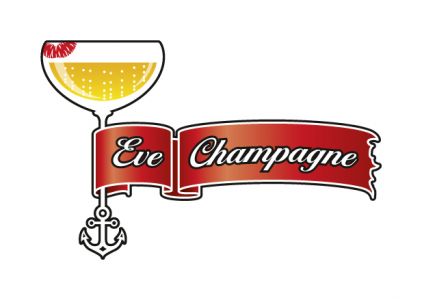
Elegante, Edel anmutende Serifenlose als Kontrastschrift.
Ich habe ein Logo für eine Tänzerin gemacht. Es ist recht rustikal und plakativ. Als Logoschrift habe ich die "Ballantines" verwendet, da sie eine kompakte Script ist.
Jetzt suche ich eine elegante, edel und wertig anmutende Serifenlose Schrit, als Kontrast zu der Scriptschrift.
Ich habe mal mit Avantgarde und Gotham herumgespielt. Bin aber nicht wirklich zufrieden. Zur Zeit tendiere ich zur Avantgarde. serifenlose Antiquas wirken generell oft etwas "unspektakulär".
Lesefreundlichkeit sollte nicht im Vordergrund stehen, da die Schrift außerhalb von kleineren Mengentexten nicht vorkommen wird.
Was haltet ihr von den DTL-Schriften Documenta, Caspari und Nobel? Würd gerne eine andere Schrift als Avantgarde nehmen...
rustikal und ballantines kannich mir zwar nicht vorstellen,
aber zeig doch mal deinen entwurf, ggf. können wir dir so besser helfen.
eine avantgarde würde ich nicht mit der ballantines mischen.
die »ballantines« ist zwar nicht der super bringer, mit der serfienlosen (ich nehme an für eine unterzeile?) kannst du nicht viel rausholen, je klasicher desto besser, ich würde die akzidenz grotesk probieren.
ohne das logo zu kennen und zu wissen was du mit zweiten schrift machen möchtest ist es aber schwer.
Jetzt suche ich eine elegante, edel und wertig anmutende Serifenlose Schrit
serifenlose Antiquas wirken generell oft etwas "unspektakulär"
sollte es nicht so sein?
Ballantines ist dafür wohl a) sehr klischeehaft und b) sehr verstaubt, aber vielleicht oberflächlich naheliegend.
Der Charakter solcher Künstlerschriften geht sehr gut mit klassizistischen Antiquas zusammen, also würde ich wohl eine ›Linearantique‹ testen, die aus dieser Form der Antiqua entstanden ist und da fällt mir als erstes die Univers ein.
Gotham geht in Richtung in Avant Garde ›ist‹ konstruiert. Wenn du sowas suchst, dann wäre die Avenir eine Überlegung wert. Im Moment sehr im Trend und mein erster Gedanke wäre die Neutraface von Houseindustries gewesen. Aber ich hätte das Gefühl, dass sich eine Univers oder eine Avenir besser mit der Ballantines vertragen würde.
Hab mich wohl etwas falsch ausgedrückt.
Ich zeige das Logo jetzt einfach:
Dass Ballantines abgenutzt und klischeehaft ist, wusste ich nicht. Dazu kenne ich mich noch nicht genügend mit Schriften aus.
Ich hatte auch überlegt, dass man die Ballantines ausschließlich im Logo behält und für Texte/Überschriften eine andere Script nimmt (Dalliance?). Denn die Ballantines hat sich schlicht gut in dem Logo gefügt, aus bereits vorher genannten Gründen (kurze Unterlängen, kompakt). Die Textschrift soll für Infotexte, Leporellos, Flyer eingesetzt werden, also Hausschrift werden.
Ich finde die DTL Nobel sehr schön (geht ja in Richtung Avenir). Die spitzen VErsalien strahlen etwas frechen aus. Außerdem erinnert mich die Condensed an Anzeigen und Plakate der 50er Jahre, was für die Figur "Eve Champagne" sehr passend wäre.
Der Begriff Tänzerin mag etwas weit sein. Sagen wir "Burlesque-Tänzerin".
was ist den das für eine tänzerin? :shock:
Schade, daß es die Elegant-Grotesk nicht digitalisiert gibt, oder?
Gruppe VI - Serifenlose Linear-Antiqua - Elegant Grotesk halbfett
D.Stempel AG, Frankfurt am Main
Erstguß 1928
Gustav Möhring
Preußischer Mann von Welt.
also mir gefällt das logo gut. das glas ist mir zwar einen hieb
zu groß ... aber darum gehts ja nicht
*
die idee mit der dalliance finde ich gut, ggf. würde ich aber den spieß
rumdrehen – also dalliance fürs logo und ballantines für headlines.
ggf. auch auf ballantines verzichten und einen mix aus dalliance +
dalliance script verwenden. das die ballantines abgenutzt ist, finde ich nicht.
da gibts andere 'englische schreibschriften' die man zu oft sieht.
eine dalliance würde allerdings dem logo mehr charakter geben.
schau dir mal die sterling von canada type an:
http://www.canadatype.com/showfont.php?id=77
die hat durch die alternativen noch mehr charakter.
* es geht ja um die textschrift.
hast du dich mal weiter bei emigre umgesehen?
eidetic neo: http://www.emigre.com/EF.php?fid=91
gibts auch als eidetic modern:
http://www.psyops.com/html/spec_eidetm.html
ich würde nicht zu neutral werden (univers, akzidenz ...) sondern
irgendetwas edles, jedoch lesbares, verwenden.
vielleicht auch die vista von emigre oder die ff strada.
nur nicht zu technisch ...
Naja, Kritik zum Logo nehme ich natürlich auch entgegen, da es durchaus noch verbessert werden kann...
Ansonsten:
Sehr schön.
Obwohl: Mir gefallen die Gemeinen noch besser als die Versalien.
Ja, die Versalien sind halt leichter zu konstruieren. Wenn ich abends mal wieder ein bißchen ausspannen will, mache ich mich mal an die Kleinbuchstaben ...
Ich versteh nicht ganz, was Du mir damit sagen willst ... daß Du mit einer digitalen Version nichts anfangen könntest, wenn es sie gäbe?